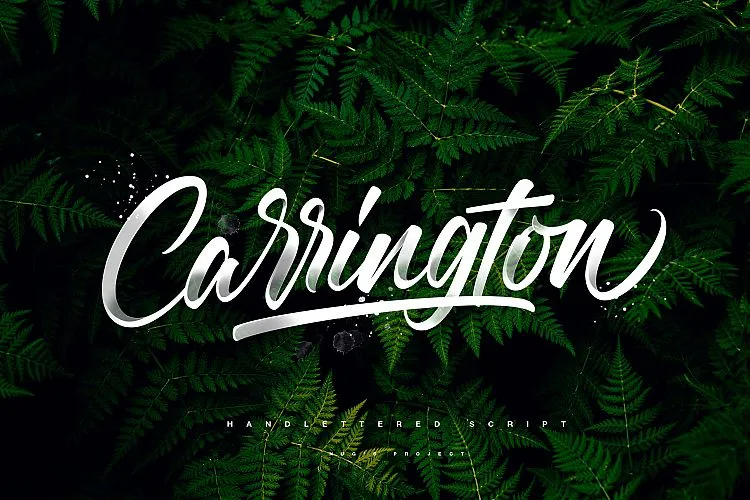
Carrington Script Font – Download Grátis
A Carrington Script Font é uma nova tipografia feita à mão por Nug’s Project que oferece um estilo dinâmico e vitalizante. Esta fonte brush script é ideal para diversas aplicações, desde títulos até selos de correspondência, logotipos, roupas personalizadas, embalagens, identificação visual em locais públicos, cartazes, selos, newsletter e até mesmo materiais publicitários. Perfeita para aqueles projetos que buscam um design único e chamativo, a Carrington Script Font é a escolha perfeita para tornar qualquer projeto ainda mais impressionante.